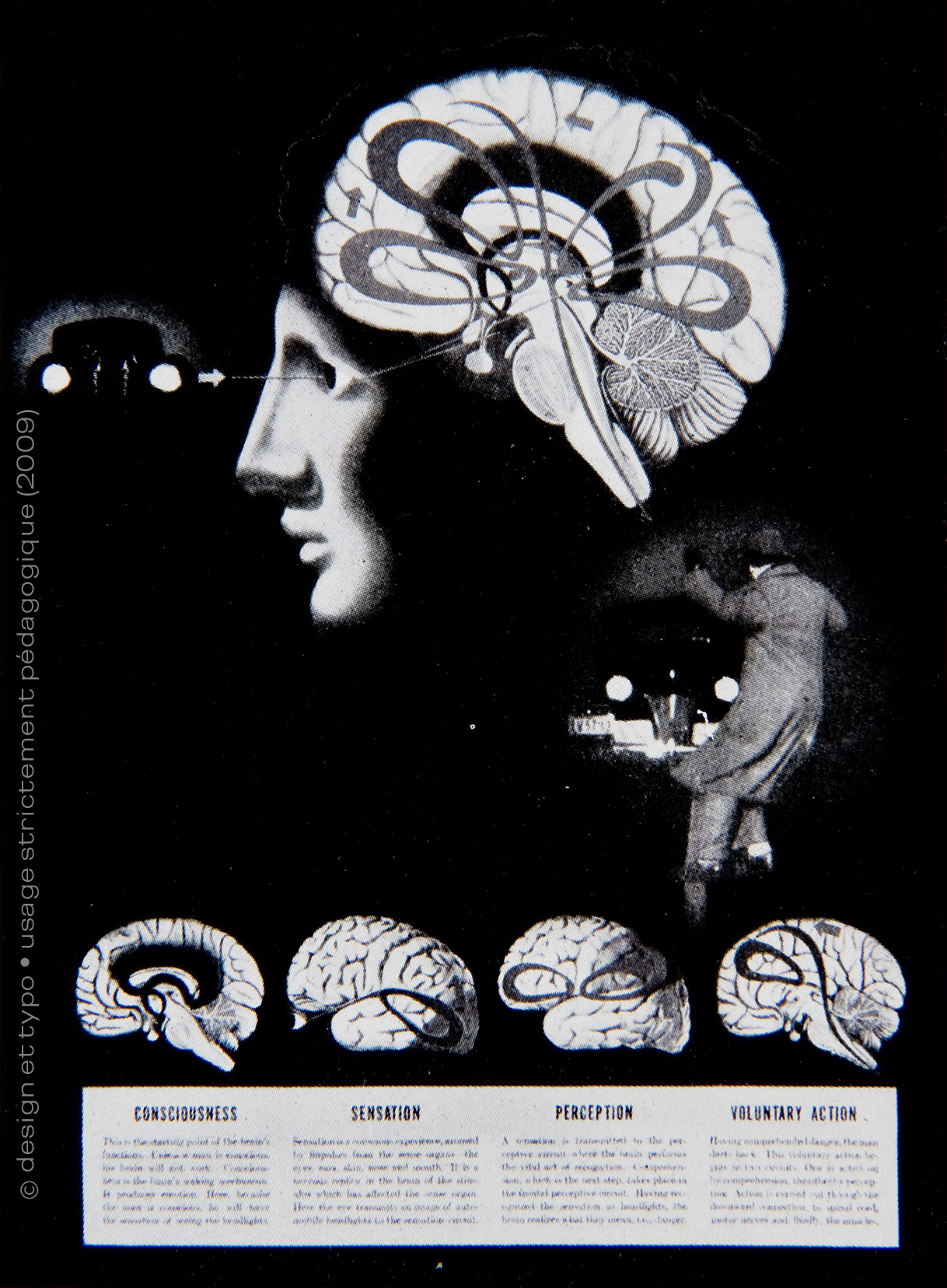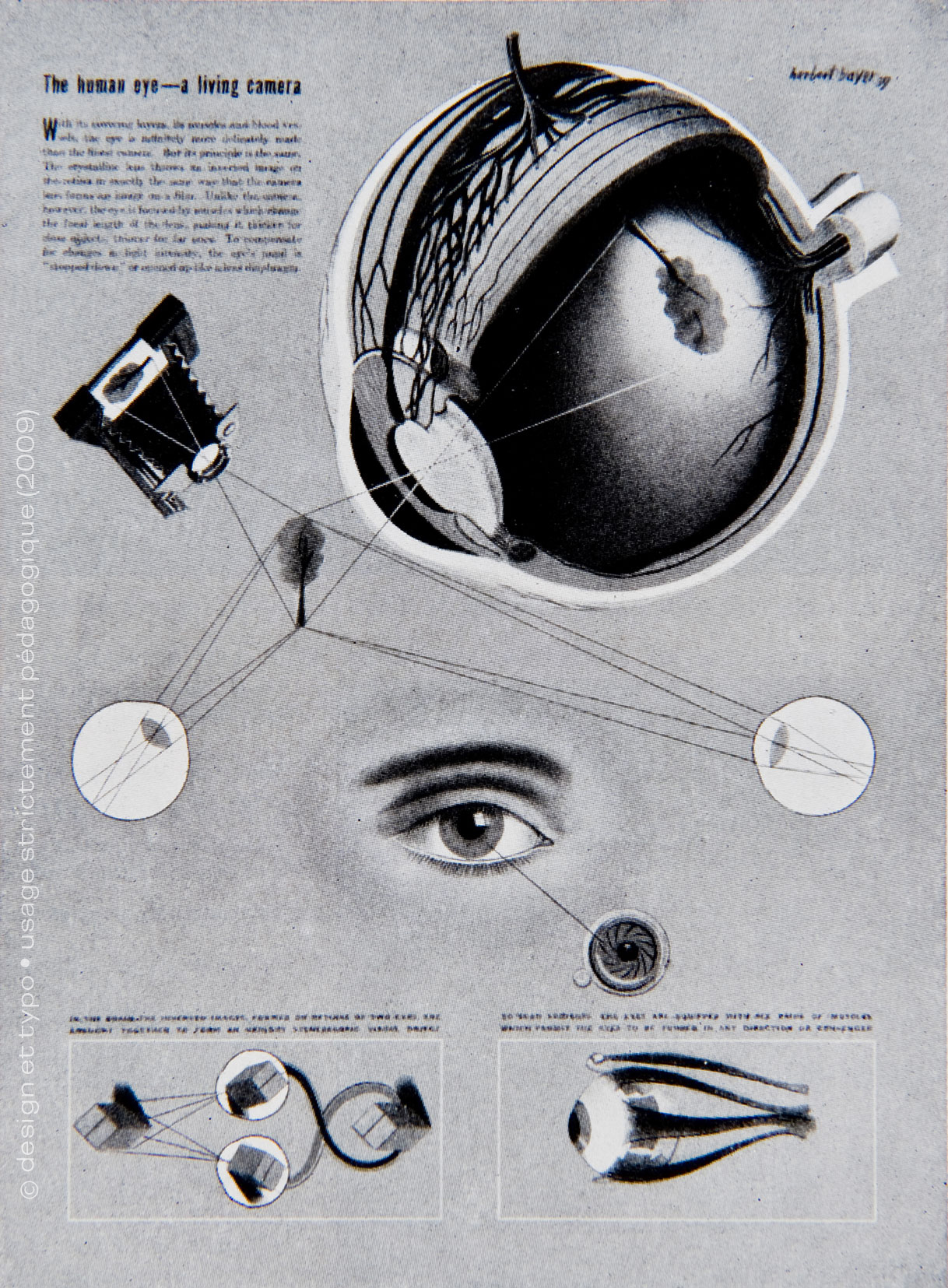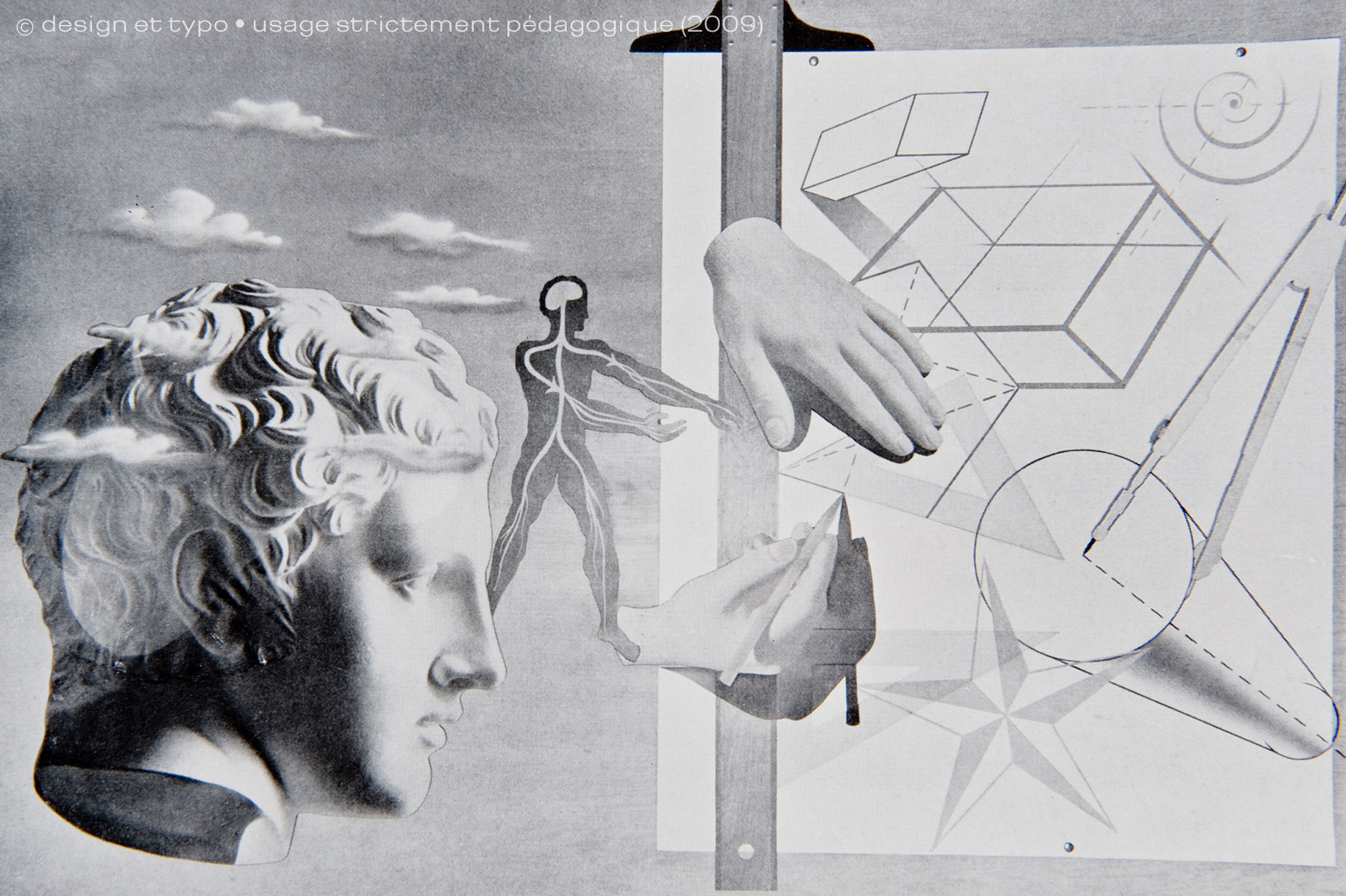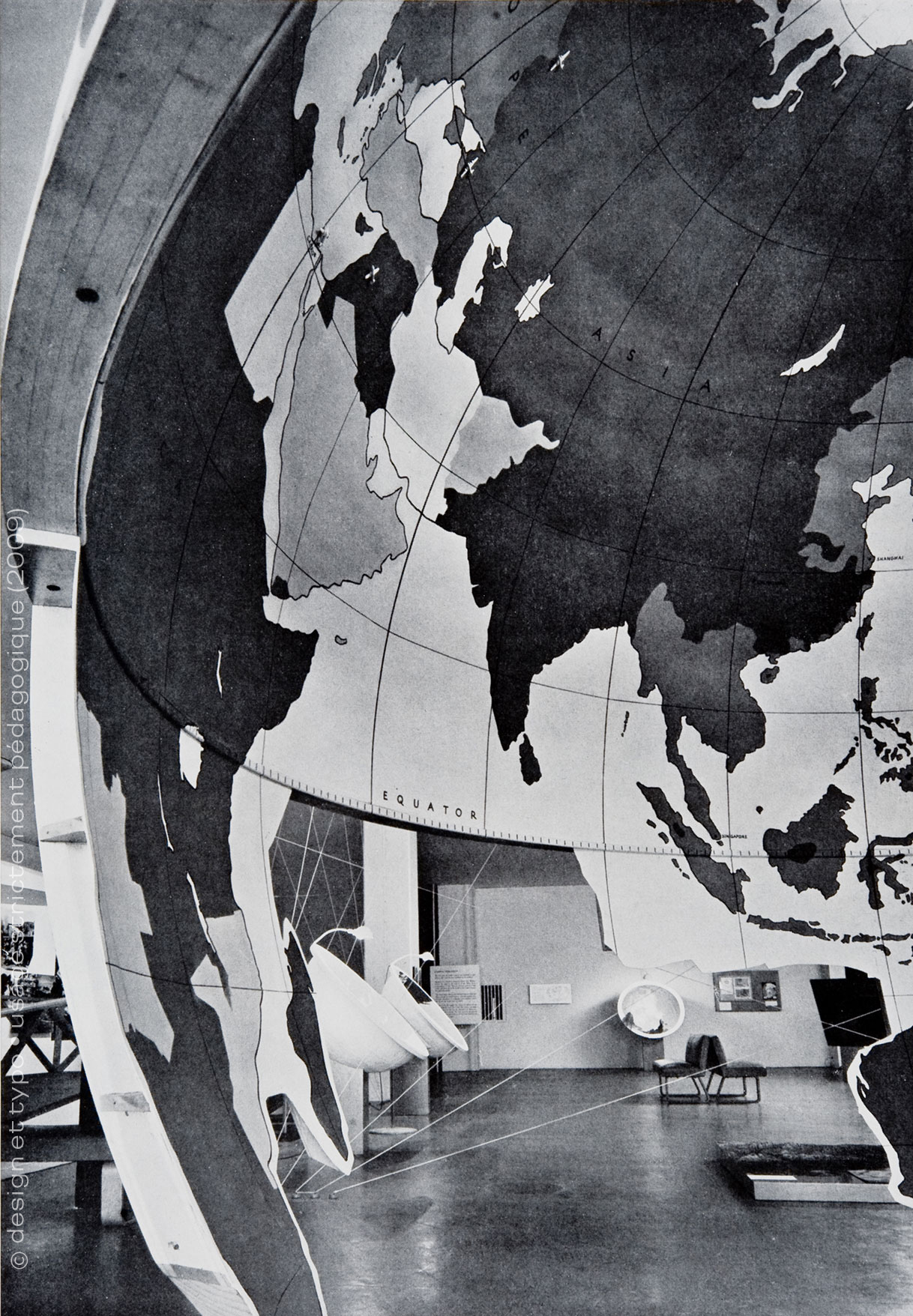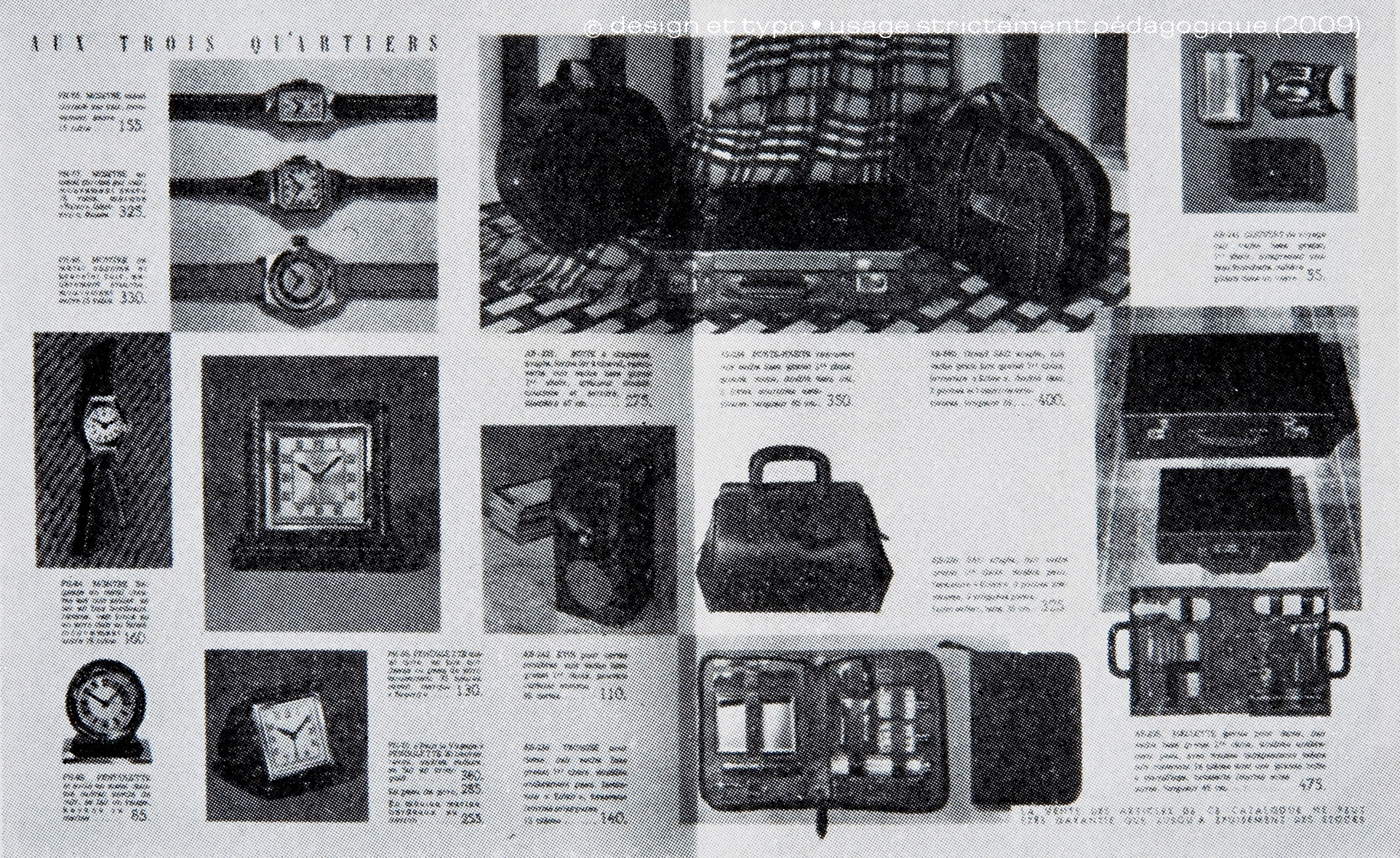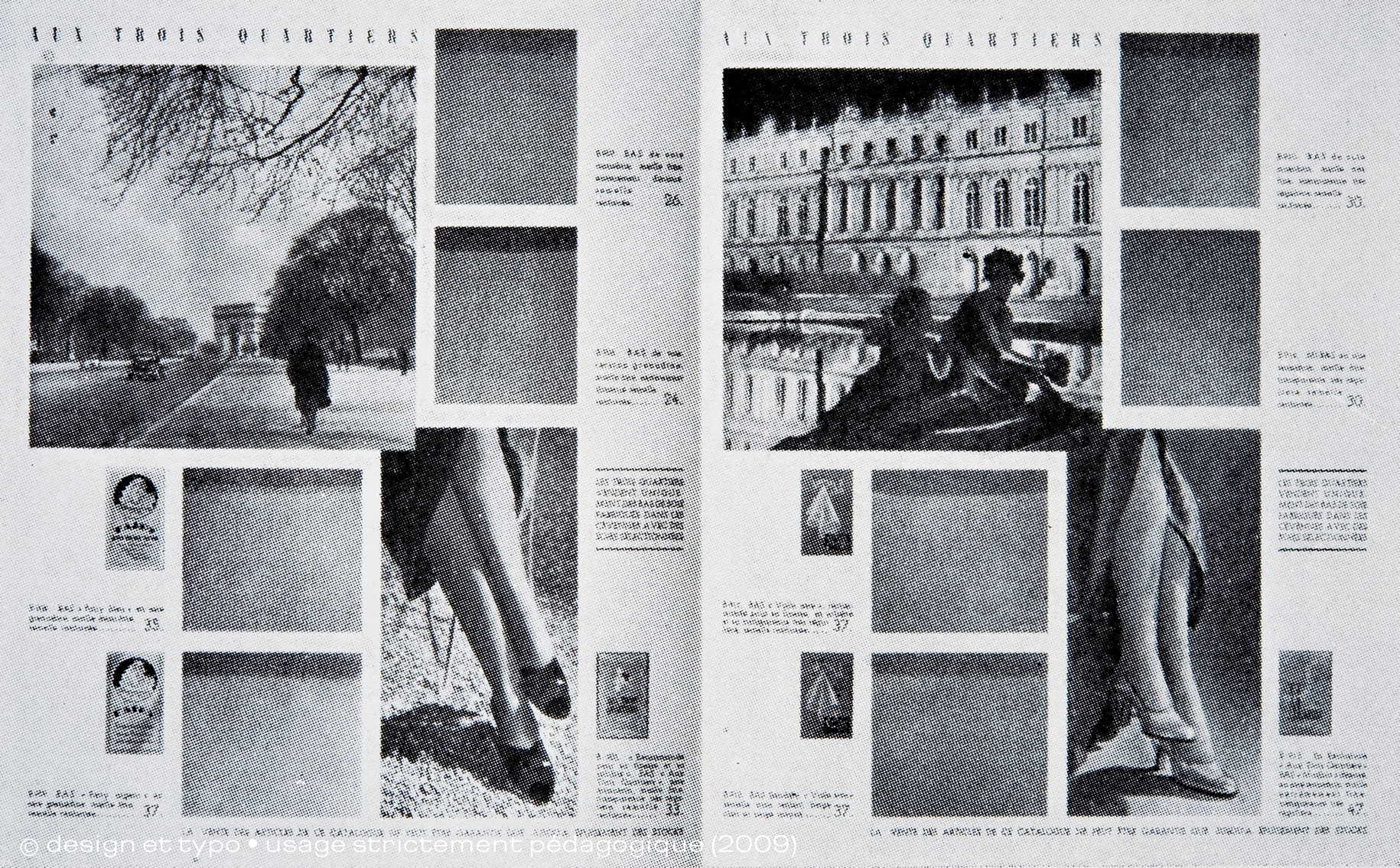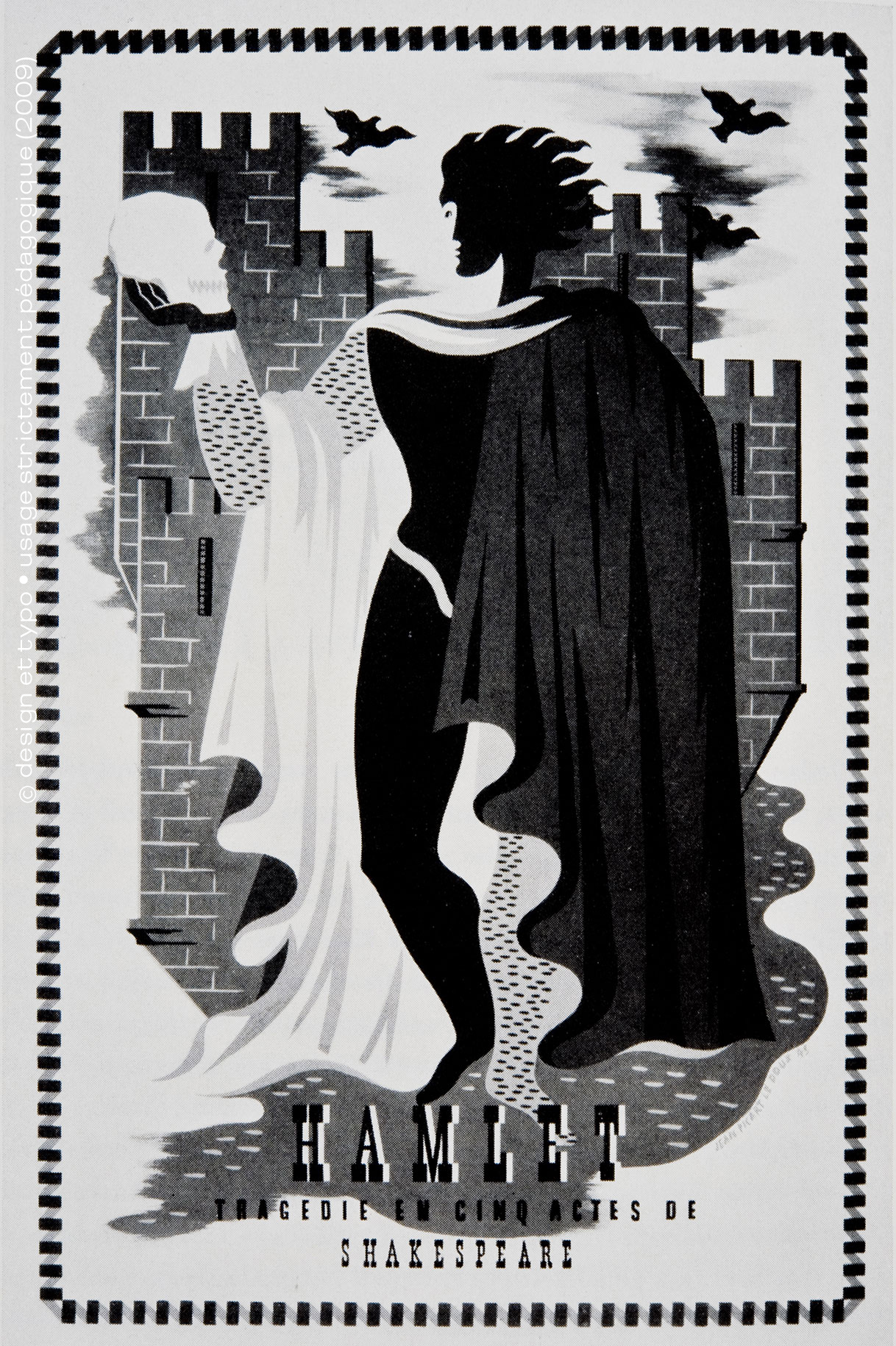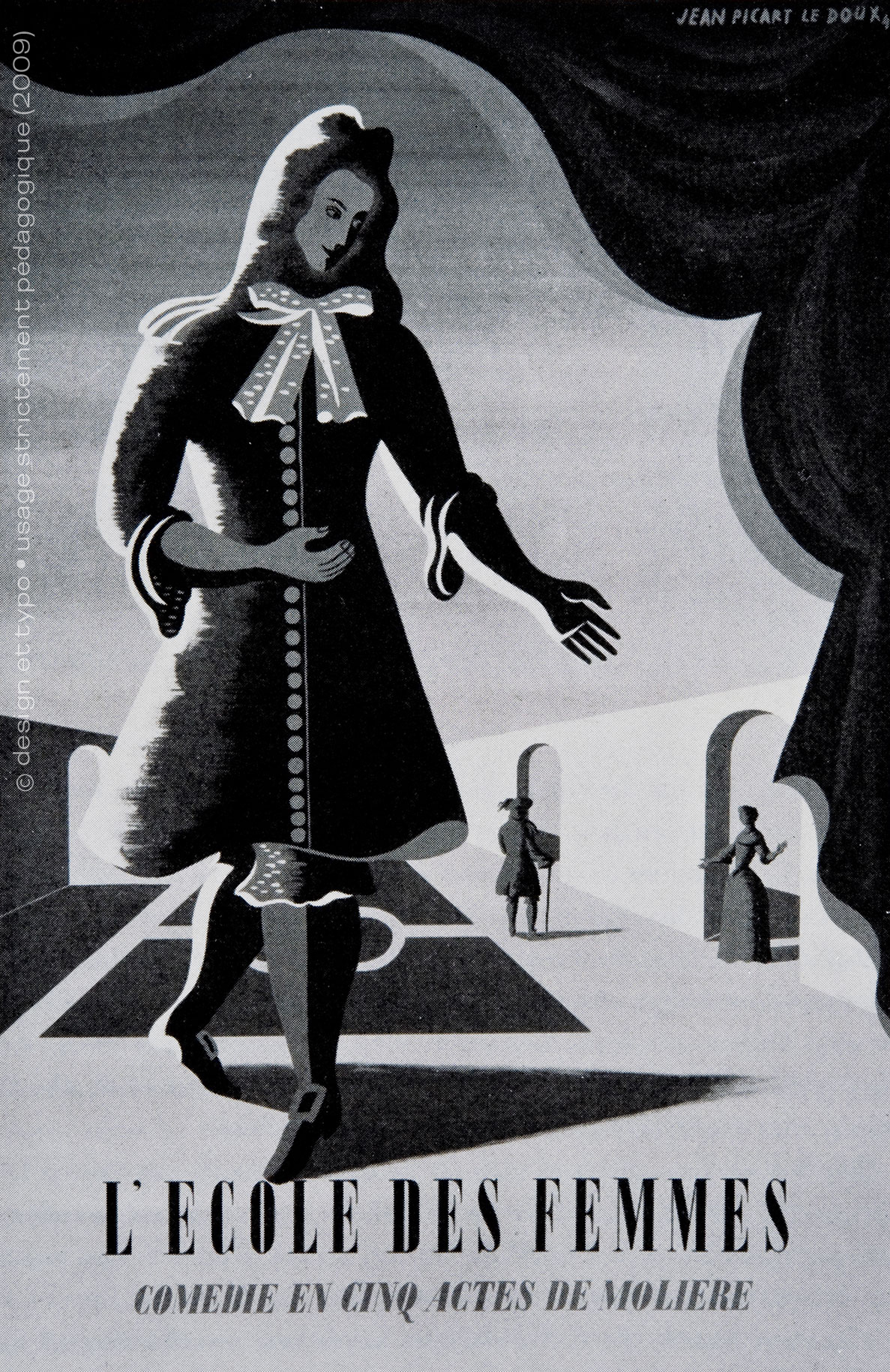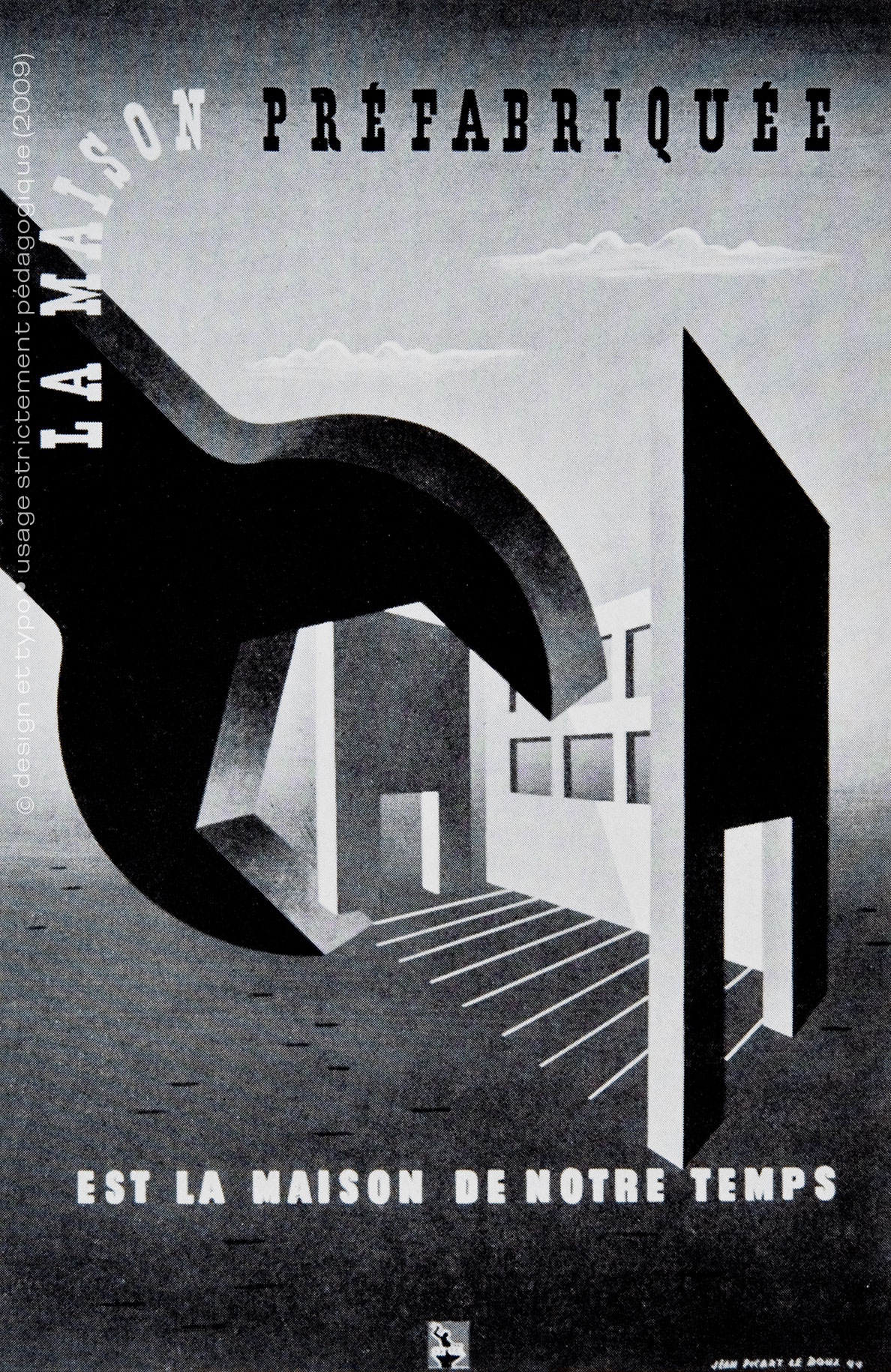
Graphis 1945 | Le processus créatif entre 1945 et 1989 (2/3)
Et en cette année 2009, alors que nous allons bientôt fêter le vingtième anniversaire de l’avènement du monde numérique moderne, nous tenions à design et typo à vous faire partager un certain nombre de documents qui attestent de la vivacité créatrice d’avant le numérique.
Ici en premier des travaux de Herbert Bayer. Ils se caractérisent par la relative simplicité, voire simplification de ses travaux, toujours structurés autour d’éléments comme le cercle, rectangle ou carré. On n’est pas Bauhausien pour rien, surtout lorsqu’on a soi-même participé à l’avenure de Weimar durant les années 1920. Mais les travaux que vous voyez ci-dessous font déjà parti de sa période américaine (lisez son histoire sur Wikipedia, il est plutôt complet). Ce style inventé par les émules de Walter Gropius, aura conquis tout de même valeur universelle. Il n’est pas une création moderne, c’est à dire actuelle qui ne se réfère de près ou de loin aux principes constructivistes énoncés par l’école d’architecture allemande. N’hésitez pas à cliquer sur chaque reproduction pour la visualiser en grand.
«Trois Quartiers» une révolution visuelle
par son nouveau directeur artistique S. Rylski.
Jean Lurçat 1936
Jean Lurçat 1937
–
Mariano Andréu 1938
M.Mathyoly 1939
D.Galanis 1938
Angèle Maclès 1938
S.Rylski
Jean Picart Le Doux
Affiche de théatre
Tapisserie, la Vigne, 1944
Affiche  de l’Office Technique pour l’Utilisation de l’Acier, 1944
Affiche pour la revue Radio 44, 1944
Prospectus pour un fortifiant, 1944
En vous souhaitant bon «visionnage» et en attendant le troisième et dernier volet de cette publication «hors normes». Surtout n’oubliez pas de cliquer sur les repros, vous en découvrirez des détails exceptionnels.